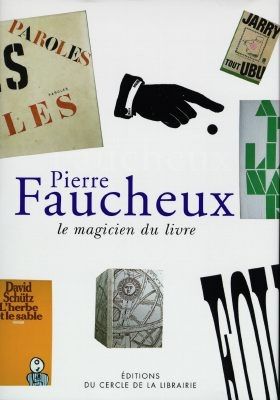
Livre neuf. Pierre Faucheux, le magicien du livre, propose un retour sur le travail de Pierre Faucheux, graphiste et typographe français. Pierre Faucheux a travaillé entre autres pour Le Club français du Livre et le Livre de Poche, et pour la plupart des éditeurs majeurs de la deuxième moitié du XXème siècle. Il a marqué de son empreinte le paysage visuel de l'industrie de l'imprimé en proposant des livres tout à la fois abordables et visuellement innovants. Le travail de Pierre Faucheux rappelle que le lecteur est aussi un esthète, et l'objet-livre un territoire potentiel d'expérimentations : le typographe, rompu à la rigueur graphique, entreprend de développer une nouvelle grammaire de l'image, inspirée de la notion d' "écart absolu", théorisée par Charles Fourier et reprise par les surréalistes, notamment comme titre de la XIe Exposition Internationale du Surréalisme, que Faucheux mit en scène et pour laquelle il donna affiches et plaquettes.
Importante source de documentation tant historique qu'iconographique, sur la figure de Pierre Faucheux, et à travers lui, sur l'histoire du graphisme et de l'édition en France.
Témoignages, textes critiques et entretien avec Pierre Faucheux. In fine, chronologie et index.
Très nombreux documents et illustrations en couleurs.